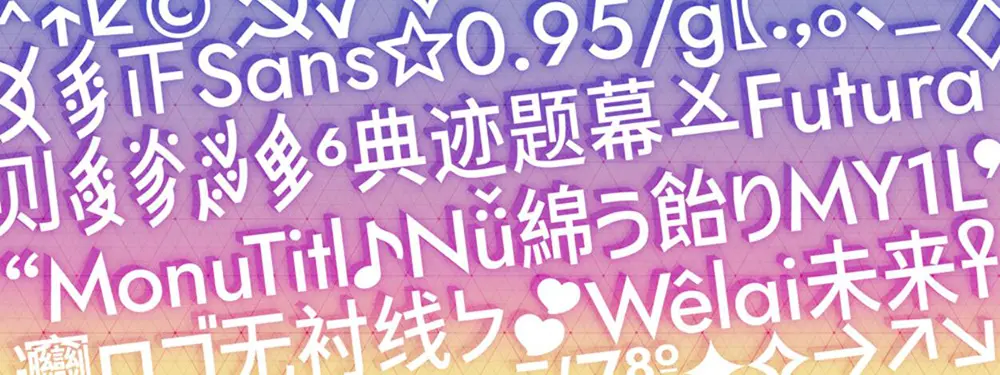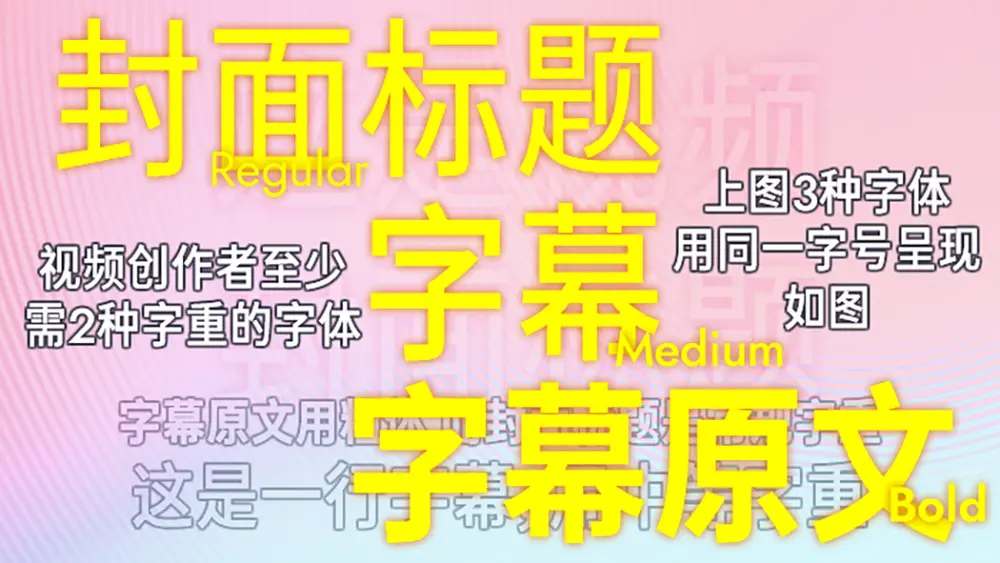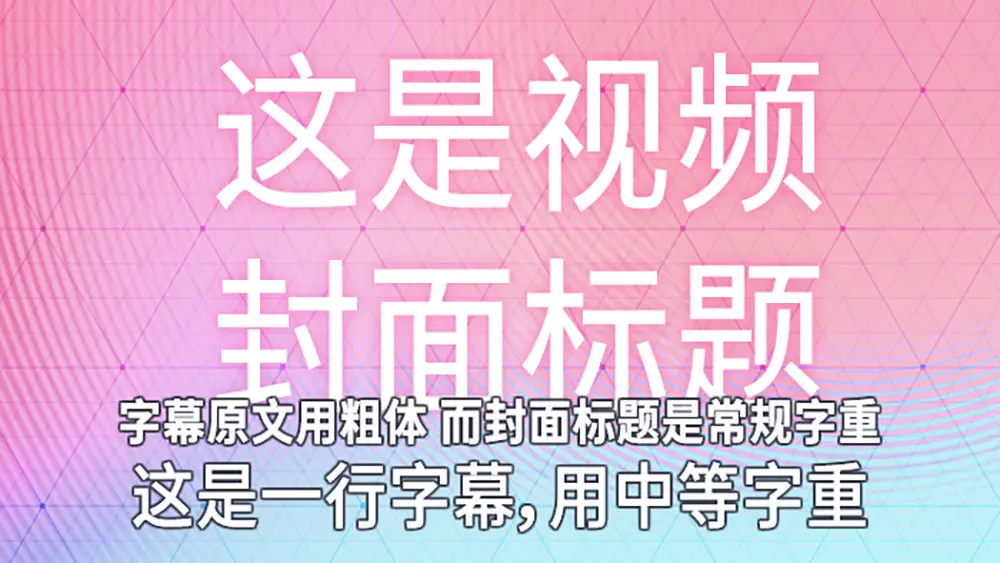
典跡題幕(MonuTitl)是一套為橫排標題、字幕設計的女書窄黑體,Titl 是 (sub)title 的縮寫,共3個字重(筆畫粗細):窄體宜讀(Condensed Book)≈常規 (Regular)、窄體中粗(Condensed Medium)、窄體粗體(Condensed Bold)。
所謂適宜標題、字幕,指字幕有不換行的需求,窄體更容易在一行裡容納一句話。為了看清字幕又需要它稍粗,但也不能是粗體,更不能是宋體等橫細字體。因此即便你不考慮方正律師函,僅有常規和粗體的微軟雅黑不適合做字幕。於是我做了這個完全 OFL1.1 授權的窄黑體,除了常規和粗體,還有介乎兩者之間的中等字重。